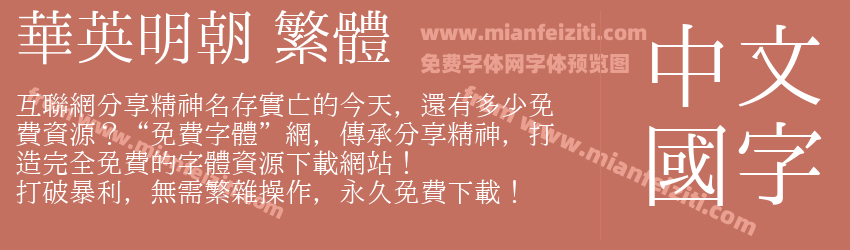
Huaying Mincho 华英明朝是一套拥有传承字形、旧字形风格的中文字体。华英明朝共提供 3 种字形风格,并带有符合 IVD_Charts_Moji_Joho 标准的异体选择器。
1. 华英明朝 旧印体
旧印刷体,字形接近新细明体(旧版)。
2. 华英明朝 传承体
传承字形,字形部件较为统一。
3. 华英明朝 旧典体
接近《康熙字典》中的字形,字形部件不统一。
4. 华英明朝 繁体
由传承体修改,可实现简入繁出的字体。